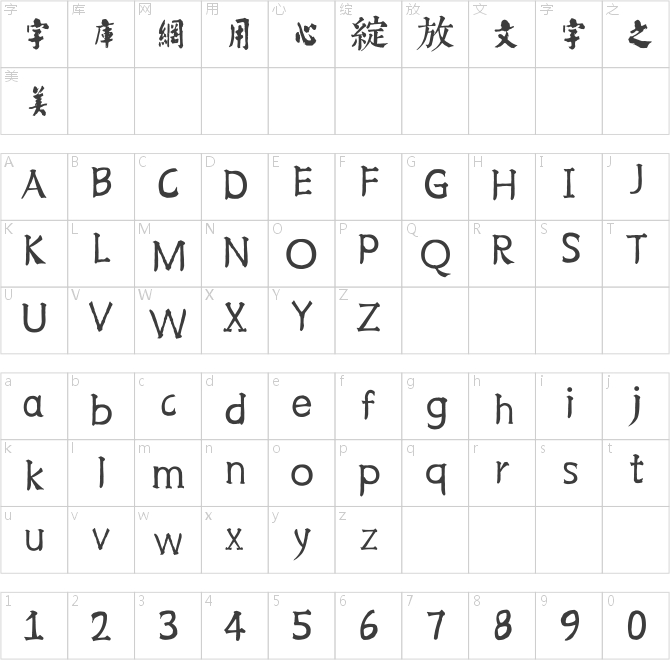
字体名称: 邯郸朱熹榜书千
邯郸朱熹榜书千字文
邯郸朱熹榜书千字文字体下载邯郸(宋)朱熹榜书千字文
邯郸朱熹榜书千字文字体邯郸(宋)朱熹榜书千字文字库是一款让人赏心悦目、百看不厌的中文字体,适合各类广告和产品包装设计应用,字体大小7.34MB,格式为ttf字体,上传用户是邯郸字库,作者/版权方为韩绍杰